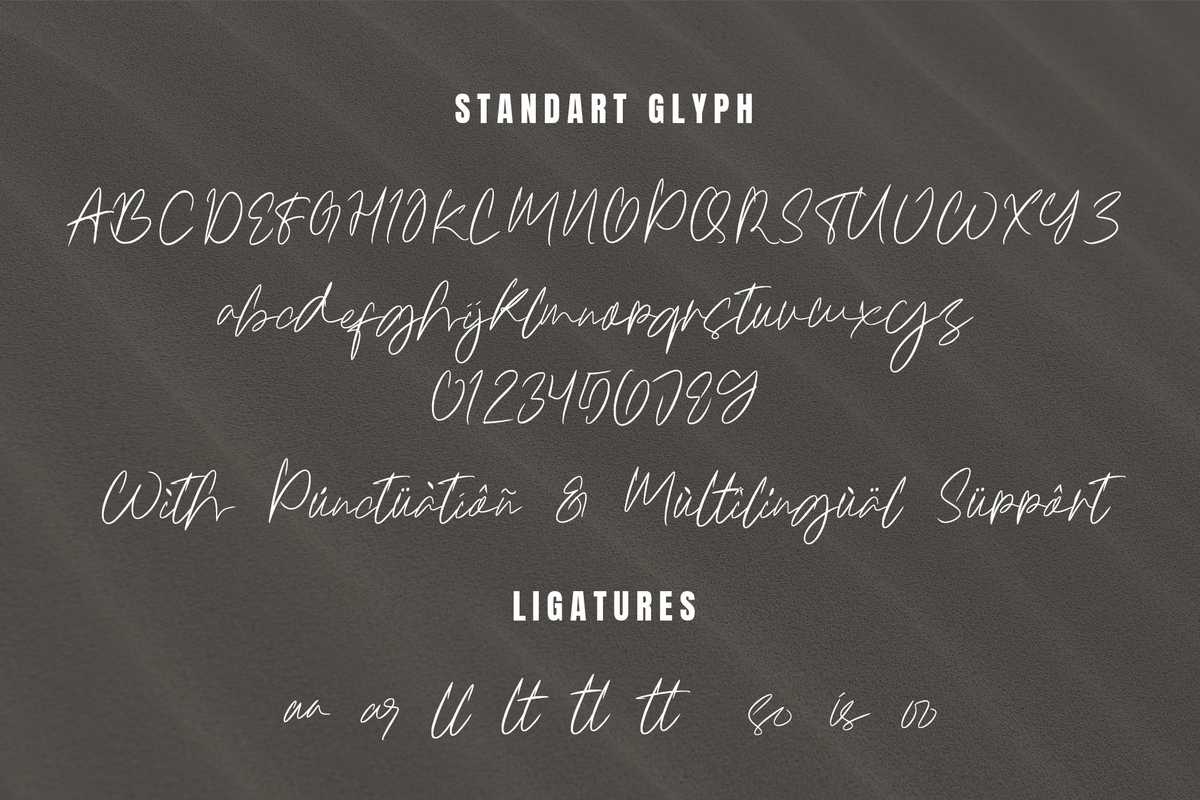
Ametta Signatures Descriptf ont是一款现代的书写、美丽的和浪漫的剪贴画。它的特点是美观、连字和涂鸦。这款字体美观、优雅,非常适合于书写项目,如增加灵感、美化运动艺术、吸引眼球的社交主题、引文、剪贴画等。Ametta Signatures Descriptf ont是一款现代的书写作品,美丽和浪漫的彩绘字体。它的特点是立体感、连字和涂鸦。这种字体美丽而优雅,非常适合于书写项目,如增加灵感、美化艺术、吸引眼球的社交主题、引用、剪贴画等等。